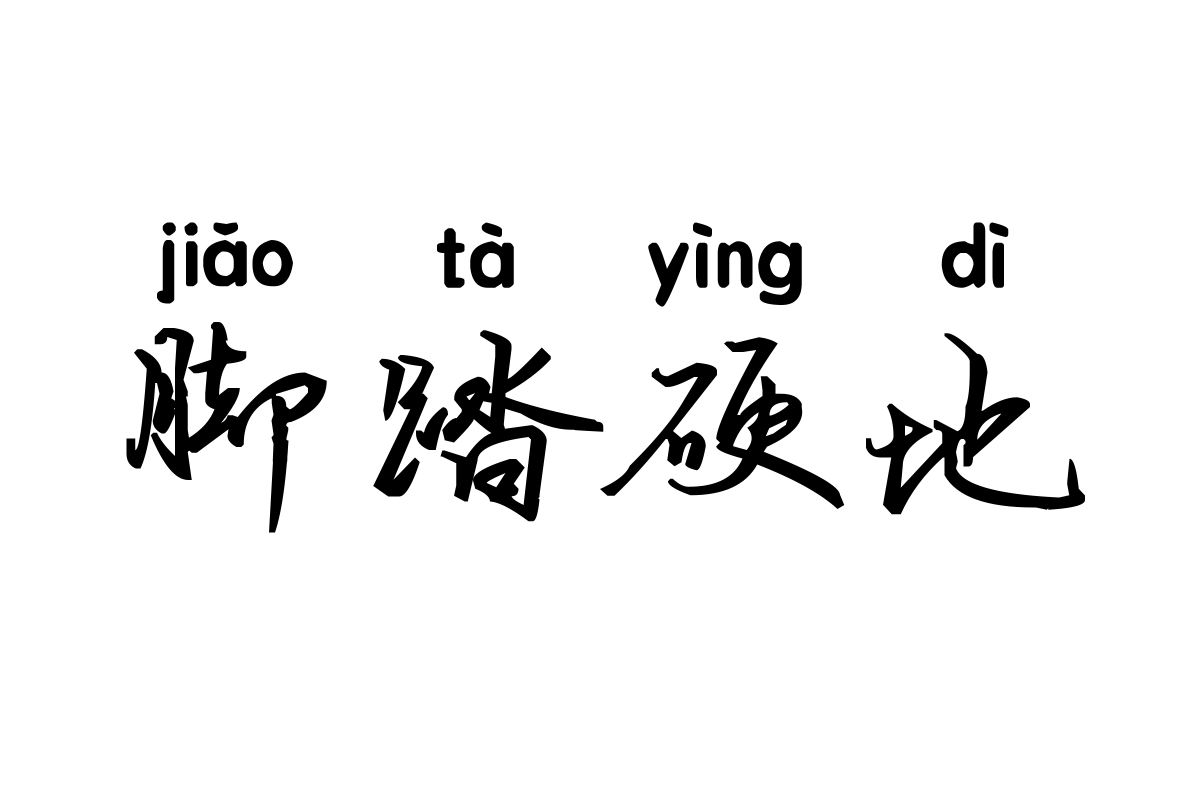
米开琳琅行书拼音体是一种独特的字体,由著名书法家米开琳创作。这种字体以其独特的风格和韵味吸引了众多书法爱好者的关注。
米开琳琅行书拼音体的特点是笔画流畅,结构紧凑。它的每个笔画都经过精心设计,使得整体看起来既有力量又有美感。这种字体的笔画粗细不一,既有直线也有曲线,使得整个字体充满了动感和活力。
此外,米开琳琅行书拼音体的字形也具有很高的辨识度。它的每个字都写得非常清晰,易于阅读。同时,这种字体的字形也具有一定的艺术性,使得整个作品看起来更加美观。
总的来说,米开琳琅行书拼音体是一种非常独特且具有艺术价值的字体。它不仅能够展现书法家的才华和技艺,也能够给人们带来美的享受和心灵的震撼。
米开琳琅行书拼音体